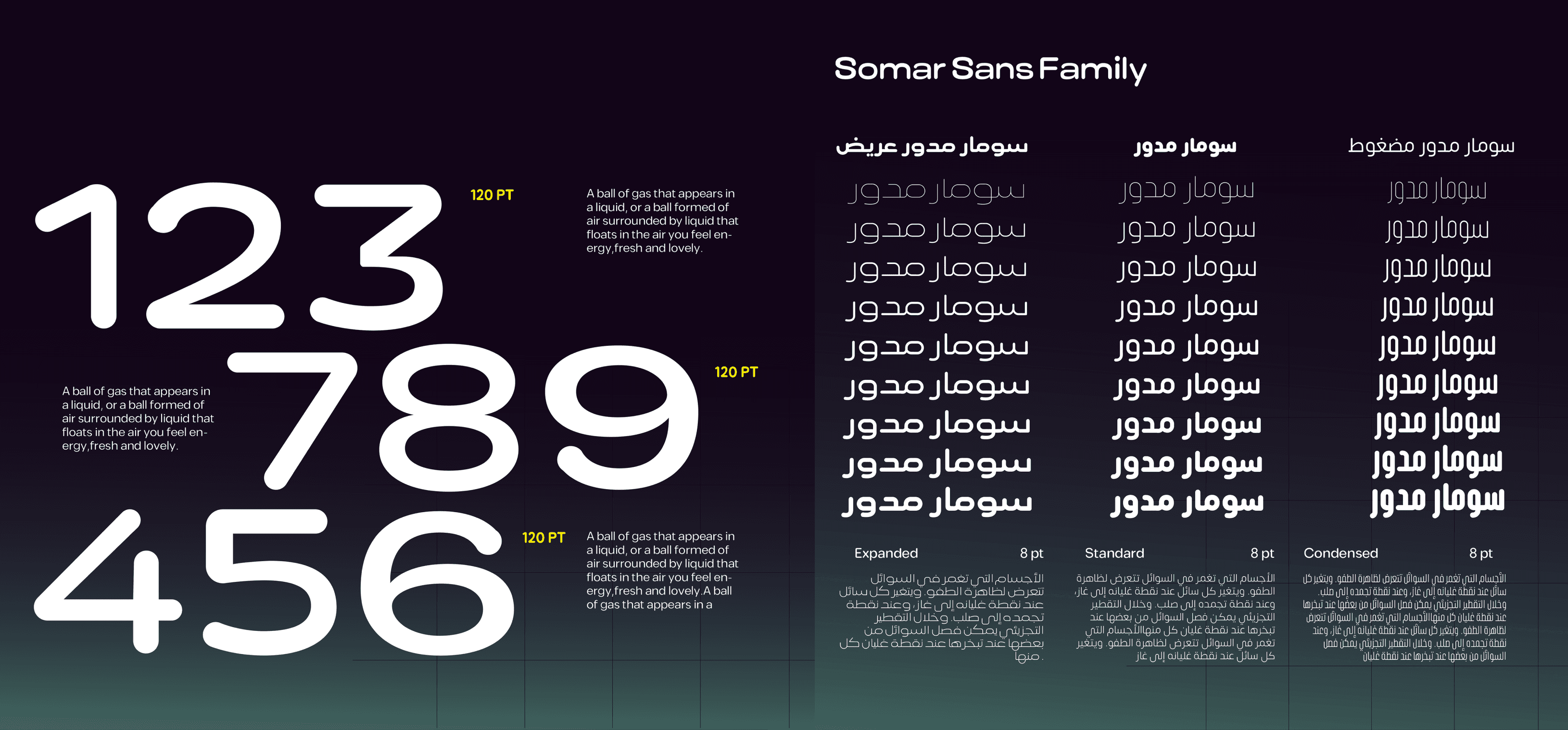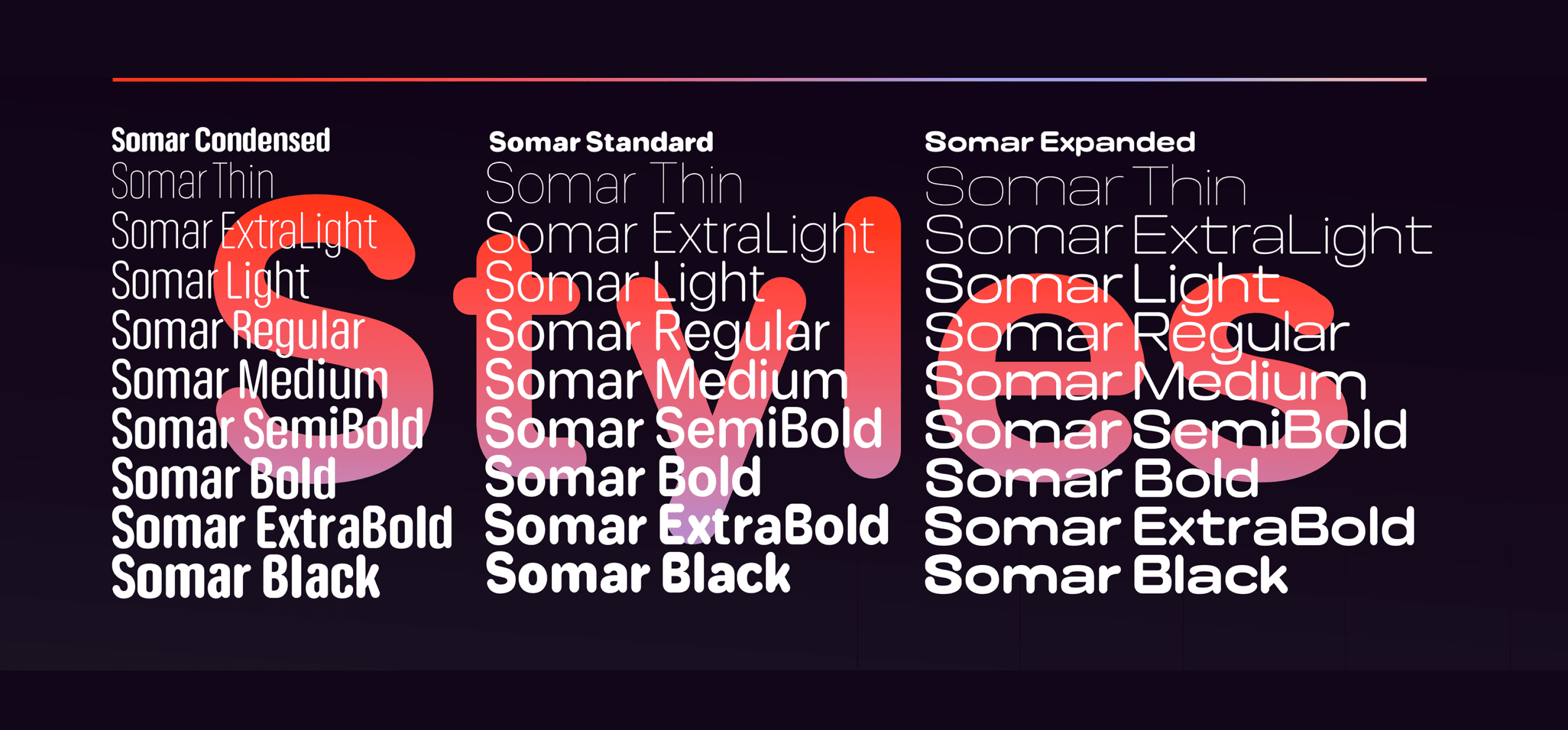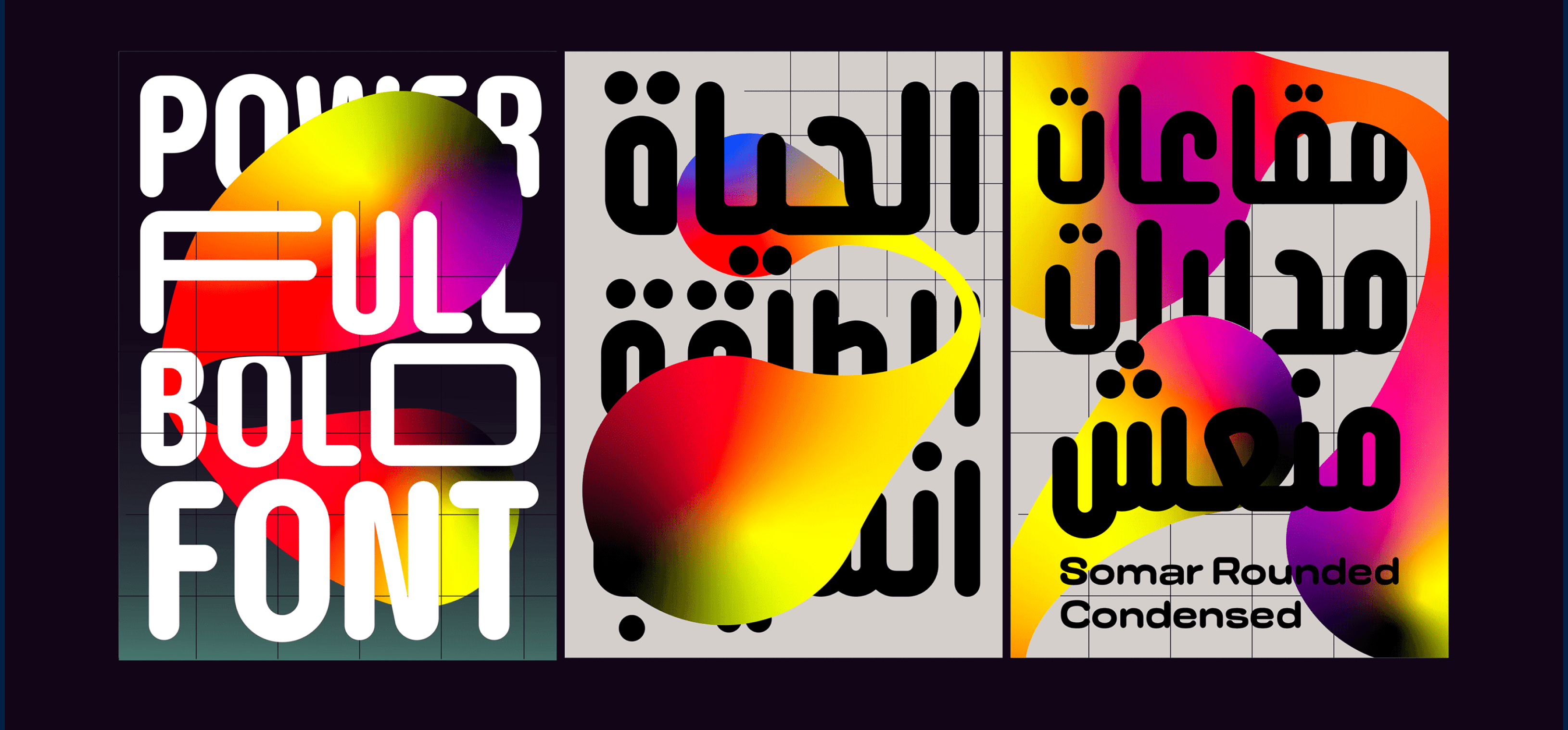
خط سومر سانس هو خط بدون سيريف بعرض متغير وممتد، من تصميم "باينات تايب ديزاين". تتضمن العائلة 54 خطًا بأنماط وأوزان متنوعة. كان هدفنا إنشاء مفهوم مرن يمكن استخدامه في العديد من الوسائط، بما في ذلك المواقع الإلكترونية، والإعلانات، والمنشورات. وقد تطلب ذلك دعم ما يصل إلى خمسين لغة تتنوع بين اللاتينية والعربية. بالإضافة إلى تقديم أنماط مختلفة تتراوح بين العادي والمضغوط والواسع. وكنتيجة لذلك، أصبح الخط مناسبًا للعناوين، والنصوص الأساسية، والعناوين البارزة بأحجام كبيرة وفي المساحات الصغيرة.